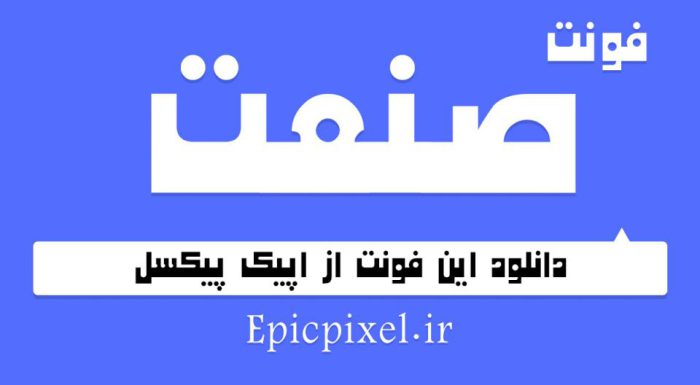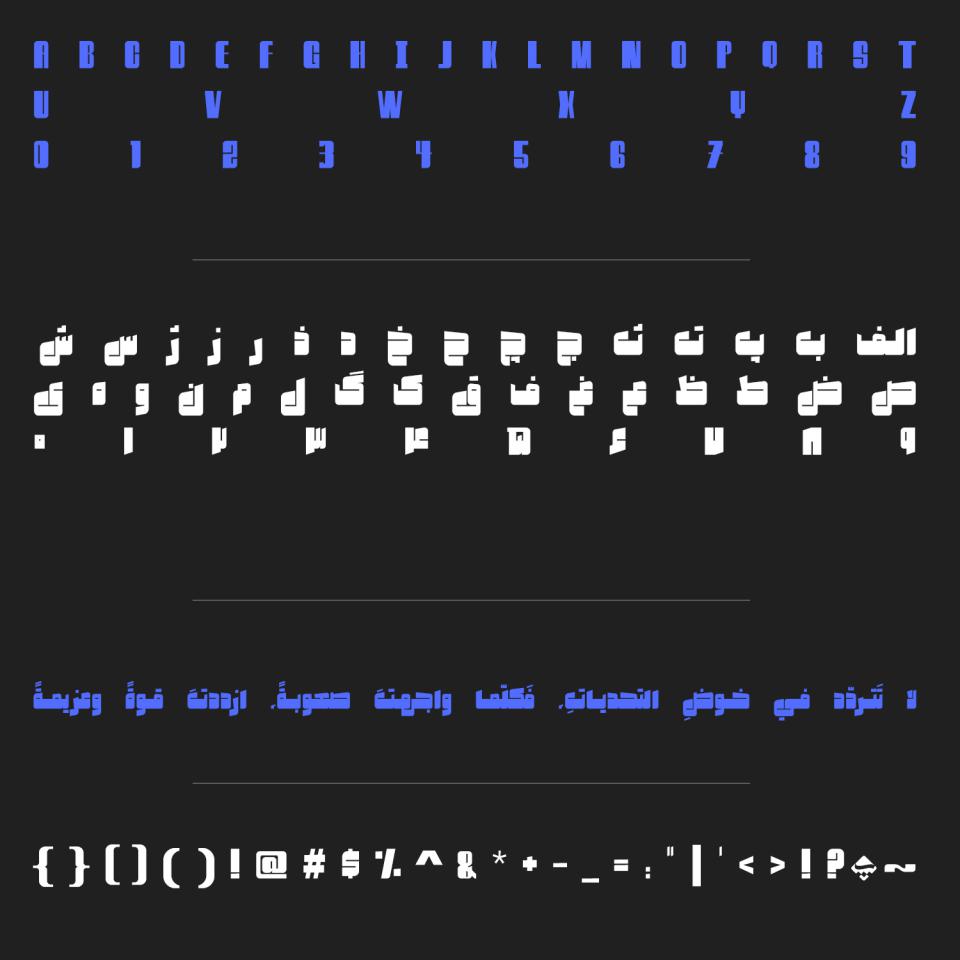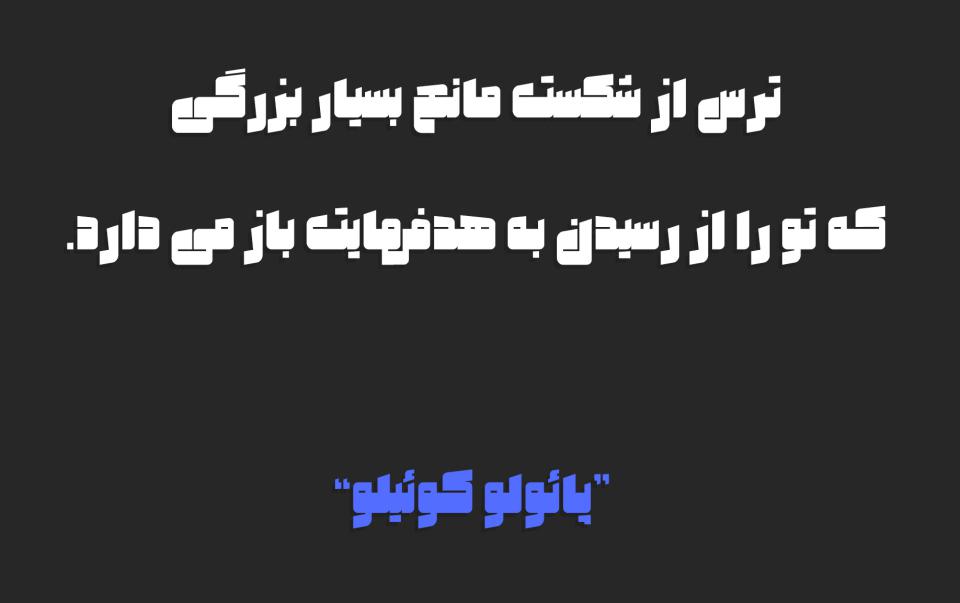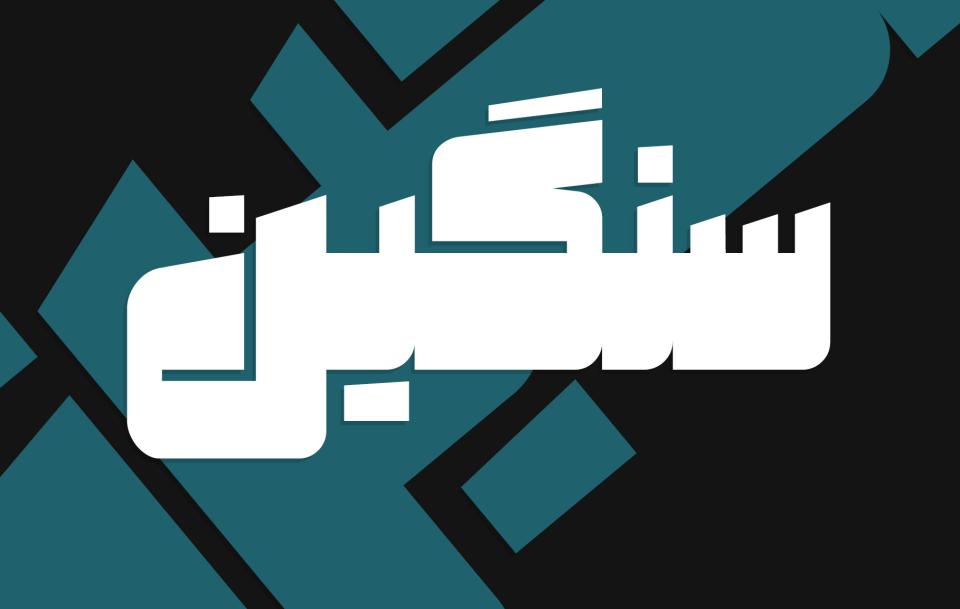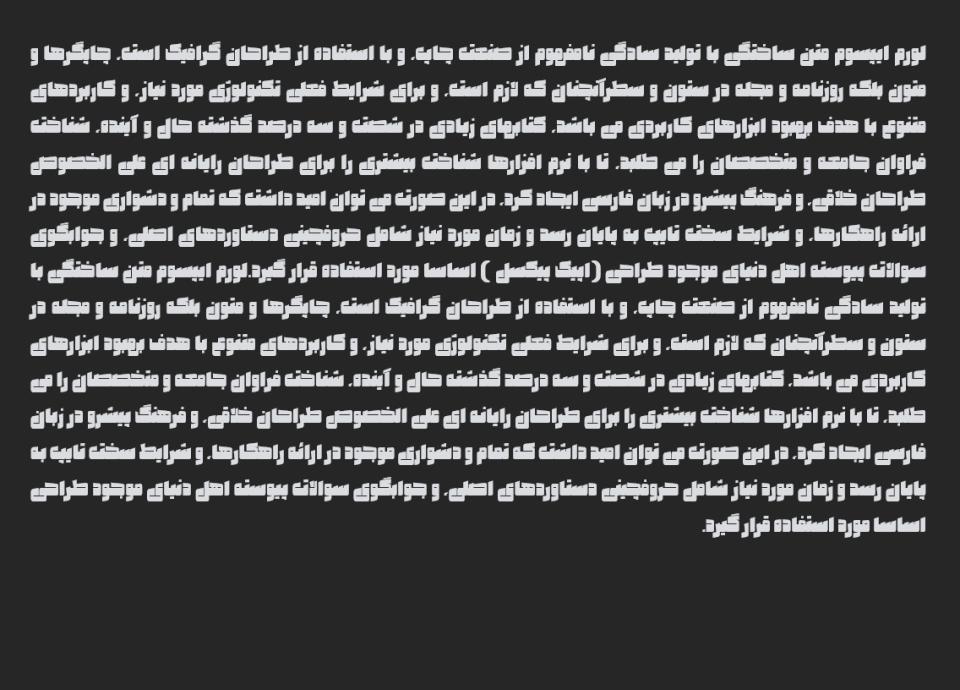
14 فونت صنعت فارسی
فونت صنعت، یه انتخاب عالی برای کساییه که دنبال یه فونت سنگین و هندسی با حس نوستالژیک هستن. این فونت، یادآور طراحی حروف ایرانی در دهه ۵۰ه، همون حروف سنگینی که بیشتر تو تابلوهای سردر و لوگوتایپ های صنعتی دیده می شدن.
یکی از ویژگی های برجسته فونت صنعت، وزن سنگین و ضخامت زیادشه که باعث میشه کلمات، جلوه ای قدرتمند و محکم داشته باشن، به خصوص برای فضاهای صنعتی. این ویژگی، فونت صنعت رو برای طراحی لوگو، عناوین و نوشته هایی که نیاز به جلب توجه دارن، ایده آل می کنه.
با وجود ظاهر مدرن، فونت صنعت یه حس نوستالژیک و قدیمی هم داره که می تونه به طراحی ها، عمق و اصالت ببخشه. این ترکیب منحصربه فرد، فونت صنعت رو برای پروژه هایی که می خوان همزمان حس مدرنیته و سنت رو منتقل کنن، مناسب می سازه.